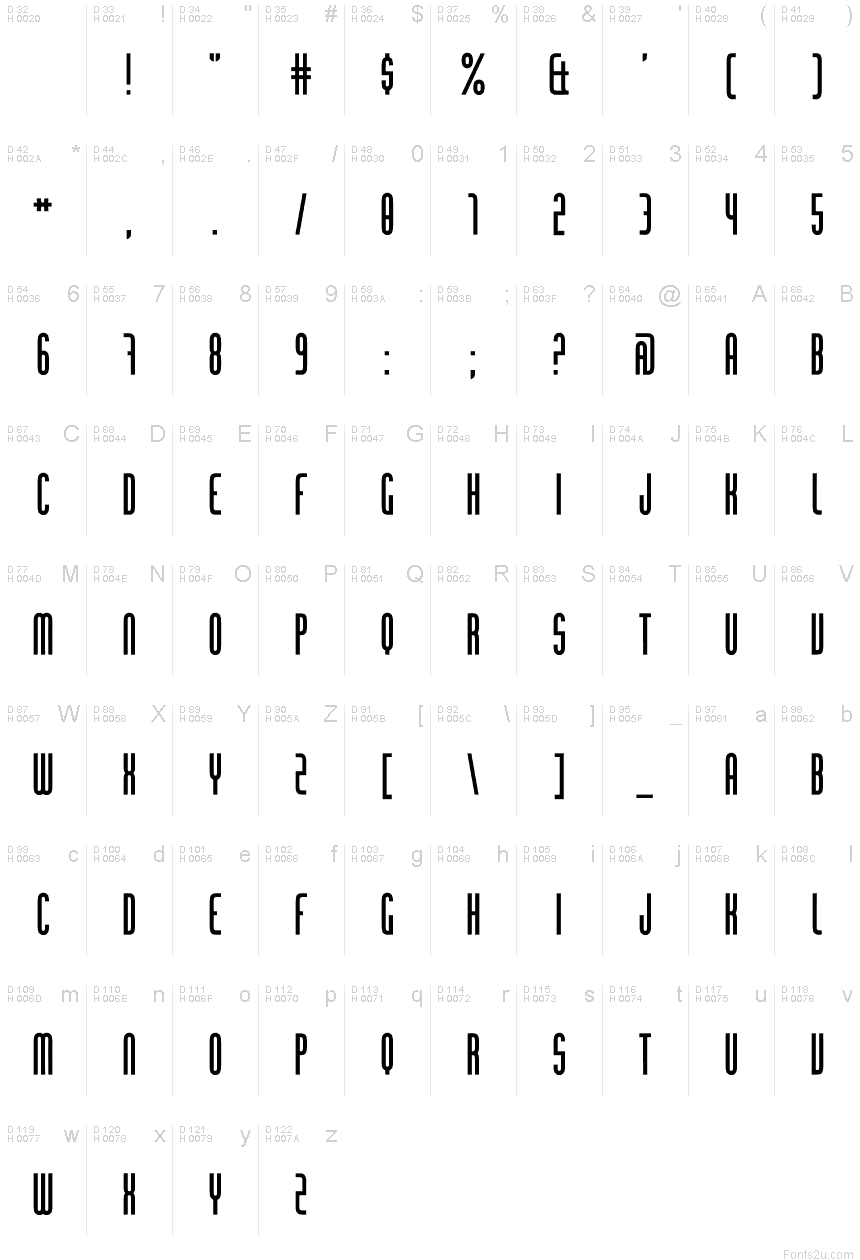
Chingolo Pro di Matrerog è un carattere sans serif condensato gratuito, caratterizzato da una presenza slanciata e imponente. Le lettere si ergono come travi d'acciaio, ma con angoli leggermente arrotondati che impediscono al design di apparire freddo o puramente meccanico. Grazie a questo ritmo verticale serrato, puoi gridare forte occupando pochissimo spazio orizzontale: i tuoi titoli e nomi risulteranno chiari e leggibili senza appesantire il layout.
Con Chingolo Pro puoi creare titoli d'impatto per poster, flyer, copertine di libri, album, packaging e grafiche web. I tratti lunghi creano un potente effetto «skyline», particolarmente incisivo in maiuscolo e nei grandi formati. Questo font gratuito si abbina perfettamente a una sans geometrica essenziale o a un carattere di testo pulito impostato in corpo minore, lasciando che Chingolo Pro catturi l'attenzione mentre il font di supporto si occupa della lettura.